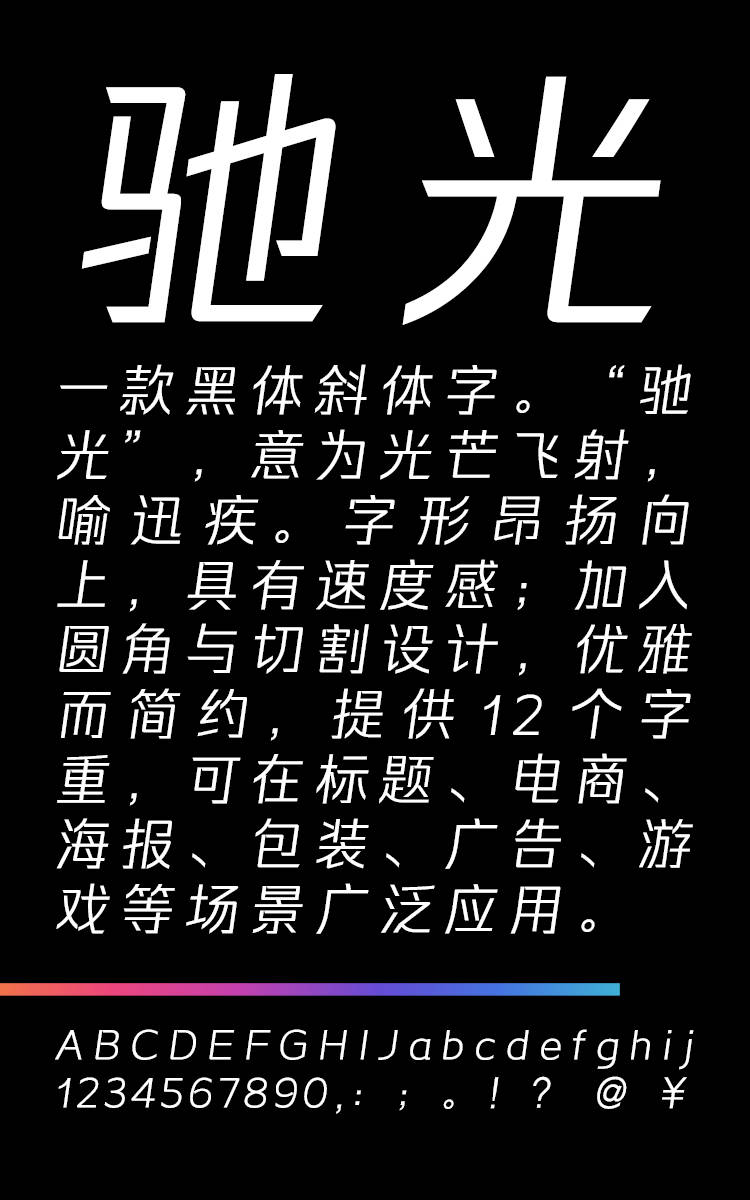
锐字潮牌驰光黑 常规
锐字潮牌驰光黑 常规,这款字体结构工整、笔画清晰,兼顾美观与易读性,适用于标题、正文、海报、包装、LOGO 等多种场景。字形优雅稳定,风格百搭耐看,适配日常排版与创意设计,让文字呈现更舒适、更具质感。锐字潮牌驰光黑 常规一笔一画,皆是细节,以均衡的比例、流畅的线条打造舒适视觉体验,字形端正大气,风格简约现代。无论是商业设计、品牌宣传还是日常排版,都能轻松驾驭,让文字更有格调与力量。锐字潮牌驰光黑 常规字体下载。
一款黑体斜体字。“驰光”,意为光芒飞射,喻迅疾。字形昂扬向上,具有速度感;加入圆角与切割设计,优雅而简约,提供10个字重,可在标题、电商、海报、包装、广告、游戏等场景广泛应用。